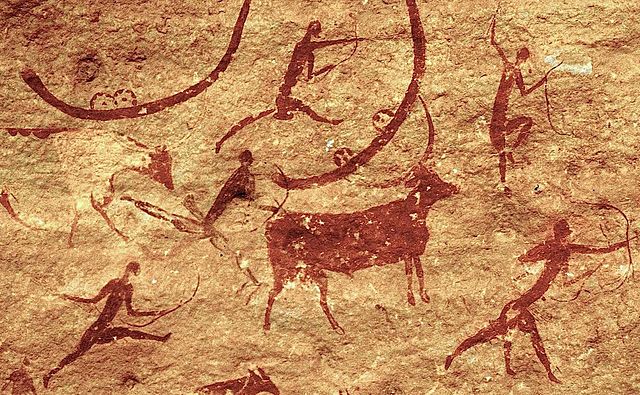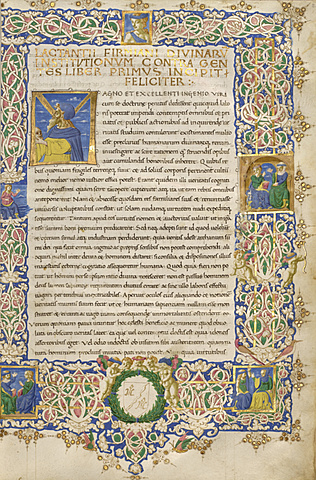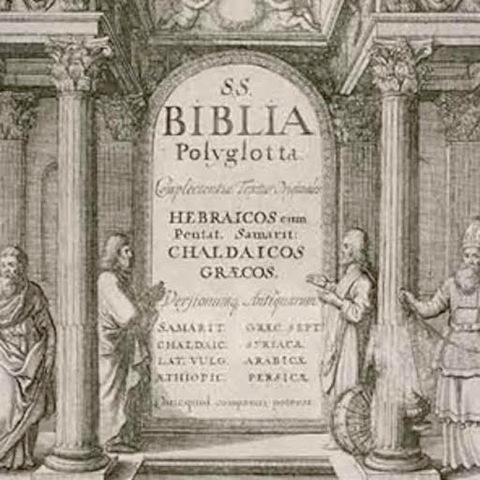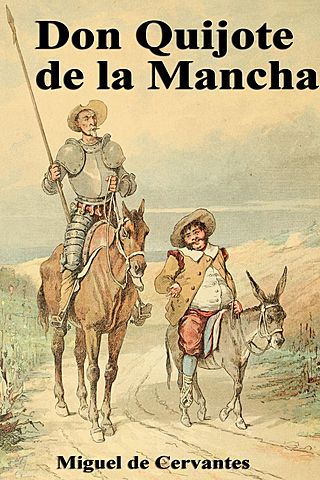
El sistema de escritura griego es alfabético y tiene su origen c. siglo XI a.C. Señalar que las primeras inscripciones son del siglo VIII a. C. El sentido de la escritura es de derecha a izquierda o en bustrofedon.
La pintura rupestre fue una de las manifestaciones artísticas mas antiguas que hayan subsistido hasta nuestros días.
Las pictofrafias son grafismos realizados sobre las rocas mediante la aplicación de pigmentos.
Es comúnmente aceptada como una de las formas mas antiguas de expresión escrita. El cuneiforme se escribió originalmente sobre tabletas de arcilla húmeda, mediante un tallo vegetal biselado en forma de cuña, de ahí su nombre.
Fueron un sistema de escritura inventado por los antiguos egipcios. Los antiguos egipcios usaron tres tipos básicos de escritura
° jeroglífica
° hierática
°demotica
esta ultima corresponde al periodo tardío de Egipto. -
Johann Gensfleisch Zum, desarrollo en Alemania una técnica para elaborar moldes de tipos que se utilizarían para la impresión de letras individuales.
Conrad Sweynheym y Arnold Pannartz, establecen la primera imprenta de Italia,e el Monasterio Benedicto de subiaco.
Nicolas Jenson, uno de los tipografos mas importantes de la historia por componer " de Praeparatione ", obra que representa el crecimiento diseño de tipos romanos
Lo Roy introdujo la imprenta en Lyon, Francia en 1473; cinco años después se imprime el libre Le mirover de la Redemption, utilizando grabados en madera importados de basilea.
William Caxton se imprime el primer libro en ingles titulado Recuyell of the Historyes of the brujas.
Creo el primer manual de escritura del siglo XVI. En 1523 publico un segundo manual realizado con bloques de madera, impresas con tipos italicos que el diseño.
fue un reformador de la lengua francesa su trabajo mas importante fue (champfleury) publicado en 1529, medita sobre la escritura, proporcion y el significado de las letras.
1530 y 1585 las novedades tipográficas tienen su origen en Francia en lo que se denomina edad de ORO de la tipografía francesa y aparte de ediciones a mano, muestra una creación de tipos verdaderamente interesante.
Blado roduce y publica II perfetto Scrittore de Giovanni Francesco Cresci, uno de los libros clásicos sobre letras.
El rey Felipe II de España comiso a Christophe Plantin para que trabajara en la Biblia Regia, la cual fue impresa en 5 lenguas.
Se imprimen los libros de bolsillo clásicos; Don quijote, de Miguel de Cervantes Sabedra. Los tipos que se utilizaron fueron grabados por Christoffel de Amsterdam.
La imprenta de la universidad de Oxford se estableció en 1667. En 1672 John Fell compro punzones y matrices holandesas.
Los XVI ordeno la creación de un comité de eruditos para la creación de un nuevo tipo que fuera diseñado bajo principios científicos . Cada letra estaba construida sobre una cuadricula que contenía 2304 cuadros, Philippe grabo los punzones.
El joven, inicio estandarizacion del tamaño de los tipos al publicar su primera tabla de proporciones en 1737.
Se grabo un tipo etrusco San serif basado en formas en 2000 años de antigüedad, probablemente fue el primer tipo de sans serif que se haya hecho, no eran novedosos, su popularidad se debía a la buena legibilidad y textura.
Fue alumno de Cottrell y exibio en 1803 por primera vez , letras gruesas, letras cuyo contraste y peso se fue incremento al aumentar el grosor de sus rasgos.
Ottomar Mengethaler invento la linopatia, maquina usada en la composicion tipografica.
Otto Eckmann creo uno de los tipos de letra mas originales que se diseño durante el "Art Nouveau" para la findidora Kingspor.
Publico su libro titulado "Zang Tumb Tumb" en 1914, donde ejemplifica su lema la palabra en libertad utilizando nuevas formas tipográficas, enfatizando el contenido del texto.
Se convirtió probablemente en el tipo mas leido a mediados del siglo, fue diseñado por stanñey morrison y victor lerdent para el periódico londinense, esta inspirado en un tipo de Latin del siglo XVII Y SE PUBLICO EN 1932.